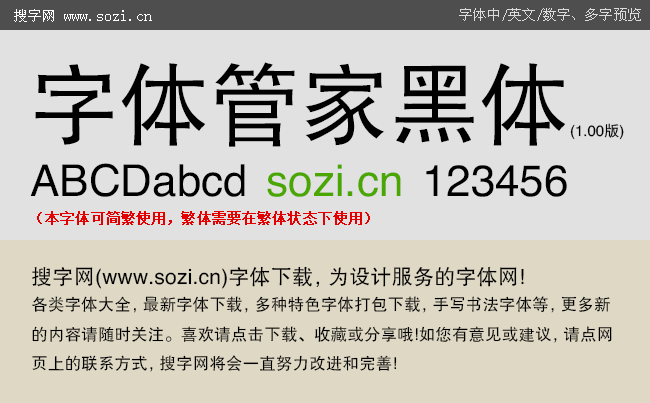
字體管家黑體
搜字網(wǎng)提供一款字體管家黑體中文字體下載,字字體管家黑體是一款字形端正的中文字體,該字體結(jié)構(gòu)簡(jiǎn)潔大方,識(shí)別性好,常用于產(chǎn)品設(shè)計(jì)、包裝印刷、報(bào)刊雜志、正文排版、繪畫創(chuàng)作等廣告設(shè)計(jì)場(chǎng)合使用。